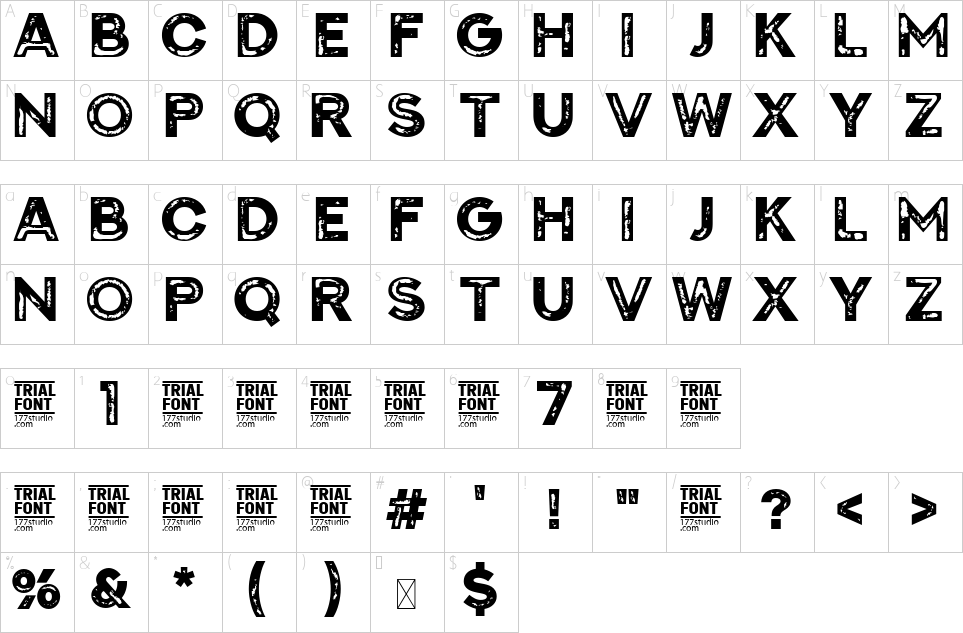
Descubra a beleza da fonte ‘Aspect’ para Windows e Mac. Desenvolvida pelo 177studio.com, esta fonte já foi baixada 2,292 vezes. ‘Aspect’ foi projetada para oferecer um estilo único e elegante, adequado para criar textos impactantes e profissionais em seu trabalho. Seja você um designer, um escritor, ou um criador de materiais digitais, ‘Aspect’ pode ajudá-lo a destacar seu trabalho. Baixe agora e experimente esse charme de letra que combina simplicidade com sofisticação.